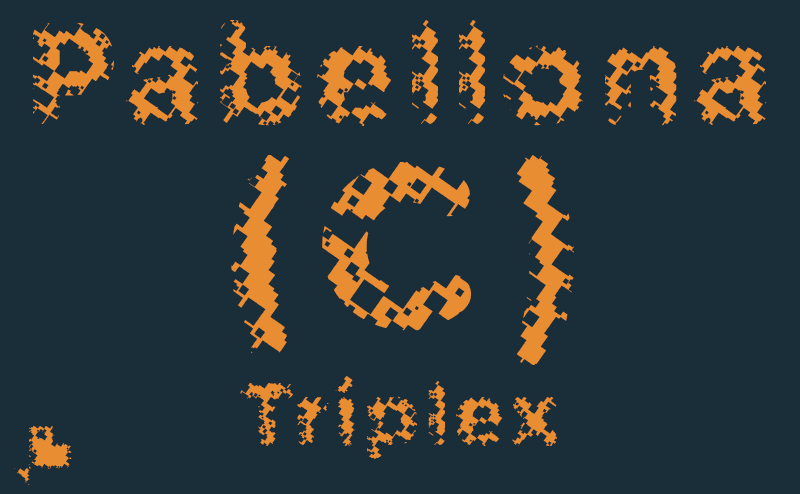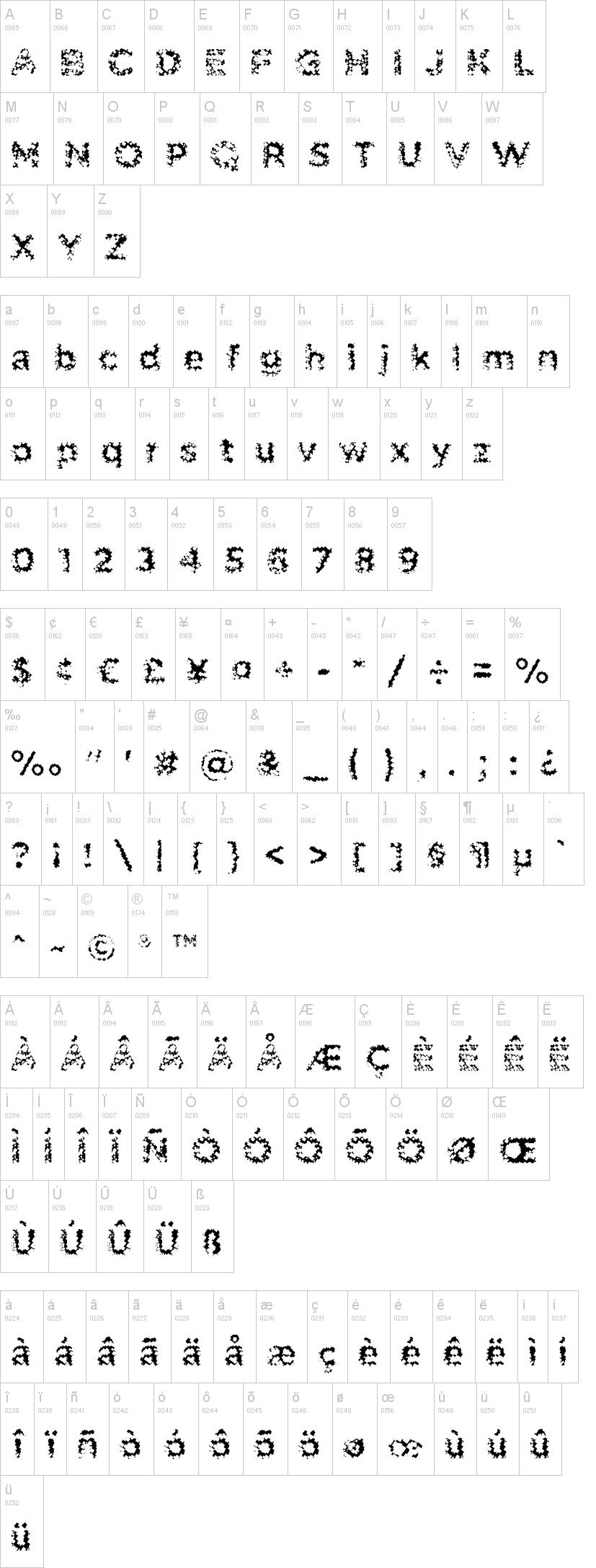
Note of the authorPabellona (C) Tríplex es la tercera fuente combinable de la serie Pabellona. Crea rótulos de texto policromados con personalidad propia.